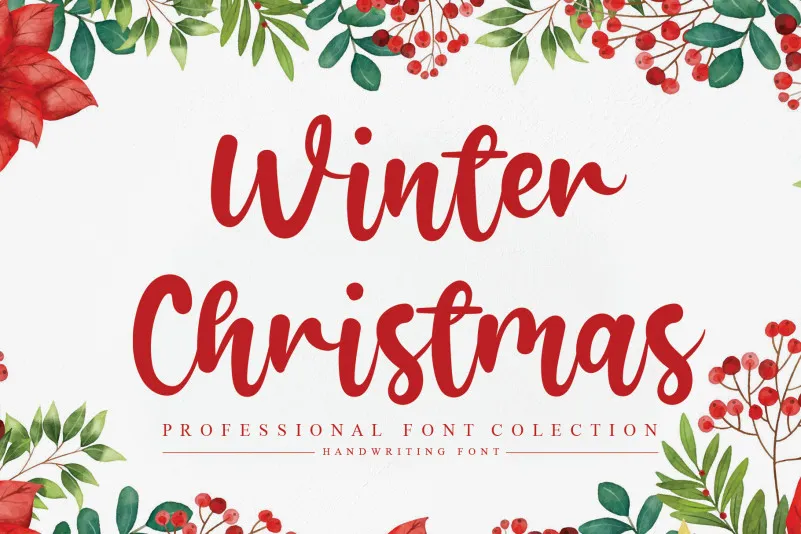
Winter Christmas Script Font – Fonte Grátis
Winter Christmas Script Font
A fonte “Winter Christmas Script Font” de autoria do designer andikastudio é uma elegante escolha para aqueles que buscam adicionar um toque aconchegante e delicado aos seus projetos digitais durante esta época de festas. Escreva, desenhe ou até mesmo desafie seu design com o charme da escrita à mão nesse script criativo. Não importa se é para cartões de Natal, calendários, designs para redes sociais ou qualquer outro tipo de conteúdo visual, essa fonte vai garantir um acabamento único e encantador a seus projetos. Winter Christmas Script Font é mais do que uma ferramenta; ela é a chave para transformar sua ideia em obra-prima. Engane-se em apaixonar-se por esta linda escrita à mão natalina e veja suas criações atingirem o patamar que sempre sonhou!